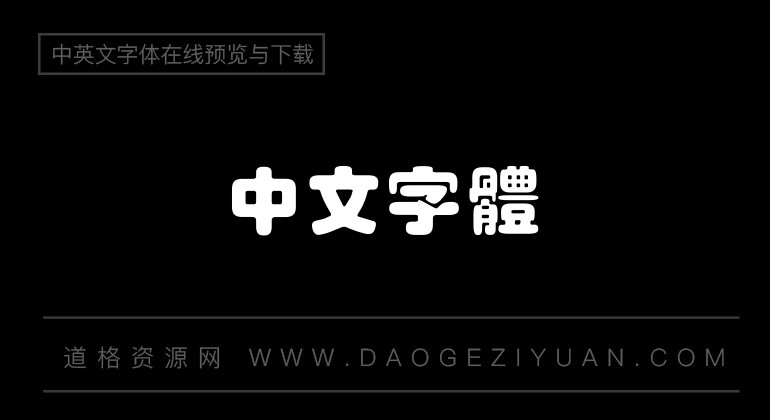
经典圆叠黑
经典圆叠黑字体是一种经典的、极具特色的汉字字体,它的特点是字体的每一个笔画都是圆形的,而且字体的每一个笔画都叠加在一起,形成一种黑压型的效果。经典圆叠黑字体具有极具特色的汉字字体,它的字体外观非常的大气,深受广大设计师的喜爱,是一种极具特色的汉字字体。
经典圆叠黑是一款非常不错的手写艺术字体,具有很好的视觉感,适合于文化类的宣传设计、商业类品牌的广告和产品包装设计以及个性化文字排版等较多场景。